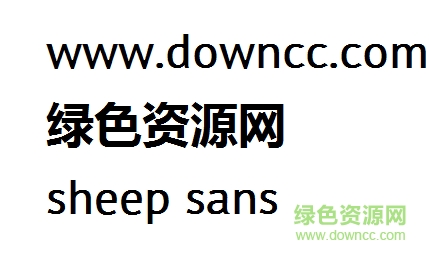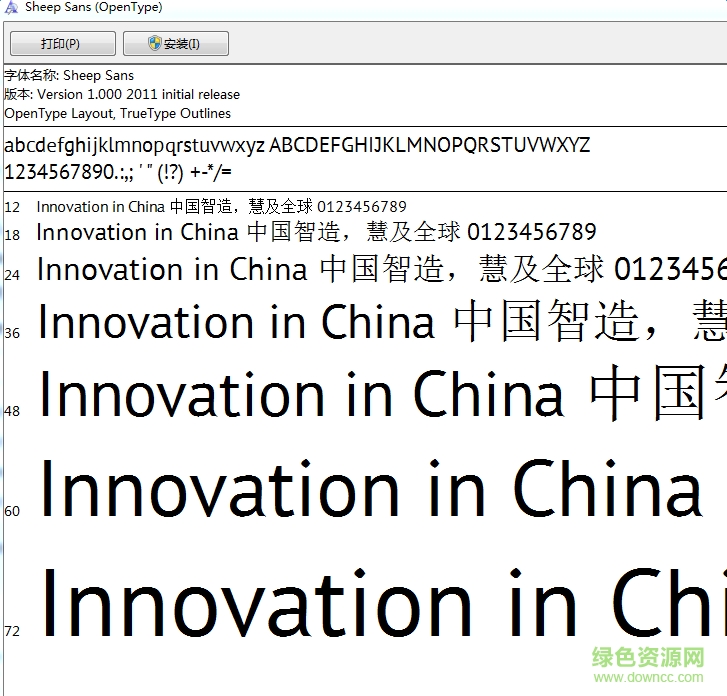
sheep sans字體是英文字體系列中經(jīng)典的一款時(shí)尚大標(biāo)題字體,線條變化自然,字形設(shè)計(jì)規(guī)范,整體雅致美觀,可應(yīng)用于時(shí)尚雜志或宣傳海報(bào)等領(lǐng)域,綠色資源網(wǎng)還有更多免費(fèi)字體下載哦!
sheep sans字體是一款深受設(shè)計(jì)師喜愛的字體,此款字體具有一定的藝術(shù)感,易讀性非常強(qiáng),字體相對(duì)來說比較完整,應(yīng)用范圍比較廣泛,喜歡的朋友歡迎來綠色資源網(wǎng)下載收藏!